В этой статье мы окунемся в историю пузырчатых шрифтов, которые способны сделать опыт взаимодействия по-настоящему увлекательным.
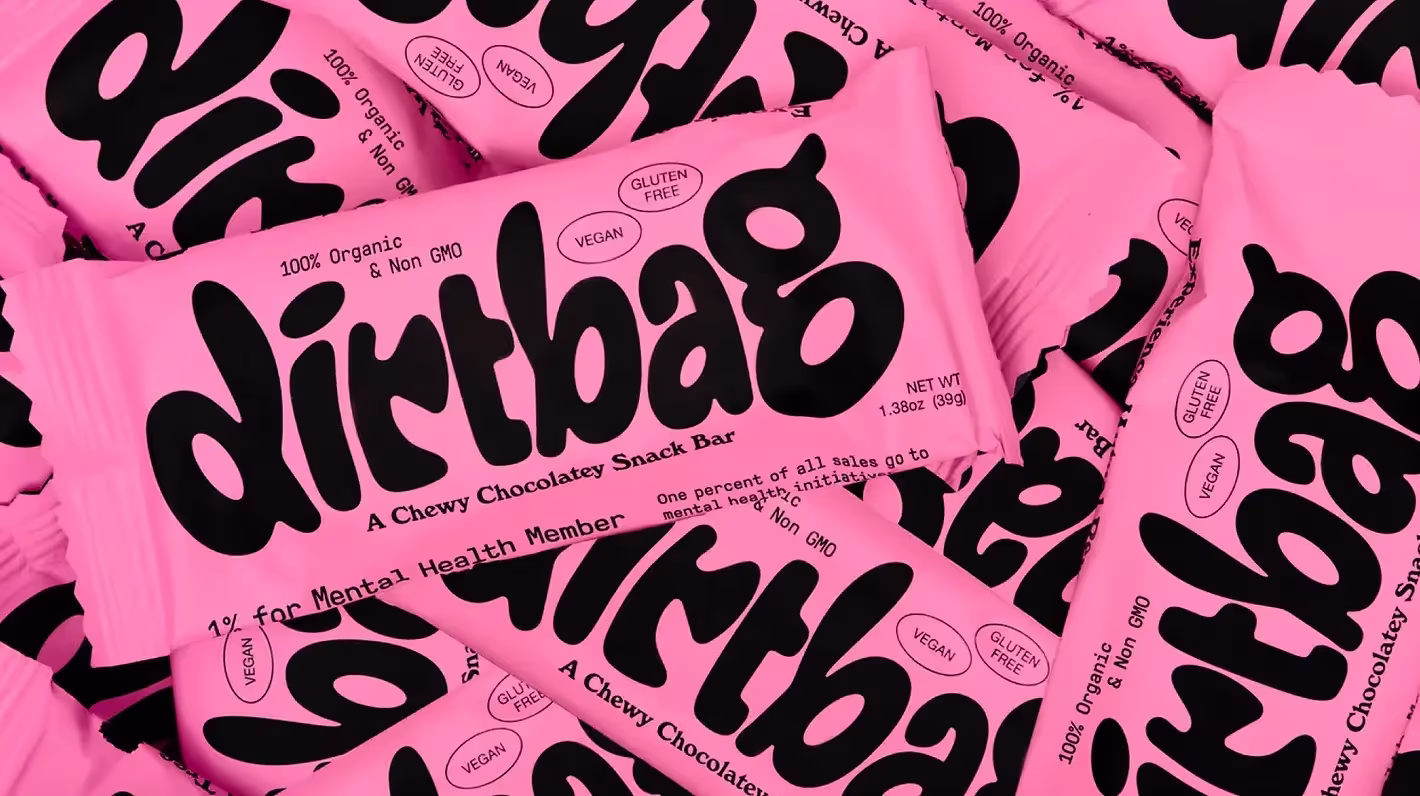
Пузырчатая типографика всех форм и размеров находится на пике популярности: приземистые надутые буквы и тягучие шрифты все чаще можно увидеть на логотипах как новых, так и уже давно существующих брендов.
Можно даже сказать, что мы живем в эпоху бума экспрессивных шрифтов. Да, многие из них состоят из округлых форм, но “пузырчатые шрифты” занимают отдельную нишу. В отличие от более обширной категории шрифтов “Югендстиль”, они почти никогда не содержат резких изгибов, узких штрихов или острых краев, которые бы уравновешивали их округлость. Они выделяются из толпы — приятные и дружелюбные на фоне откровенной серьезности брендинга прошлого десятилетия (и общего уныния пандемии).
Типографика, лежащая в основе этих пузырчатых форм, разнообразна: некоторые напоминают типичные модернистские шрифты без засечек, наполненные слишком большим количеством воздуха, в то время как другие больше похожи на традиционные рукописные шрифты, расплавившиеся под солнцем.
Эту тенденцию к более пышной типографике часто поддерживают бренды, которые используют яркие, насыщенные цветовые палитры, аналогичные округлые или пузырчатые шрифты для второстепенной типографики и другие органические элементы неправильной формы, такие как капли и волнистые линии.
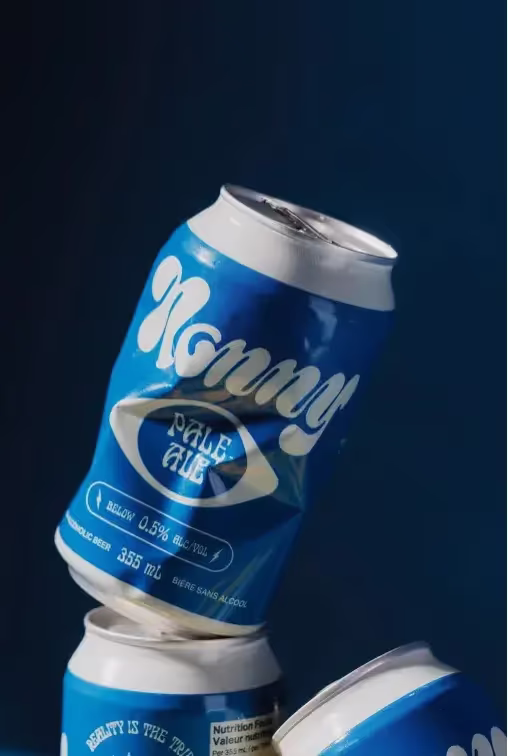
Сильное влияние на пузырчатые шрифты оказали их прямые предшественники канувшей в прошлое индустрии потребительских товаров (CPG): упаковки конфет и напитков 1970-х годов (или эпохи Вилли Вонки). Типографика того времени была уникальной и смелой, вероятнее всего, в ответ на более сдержанную эстетику середины 50-х и 60-х годов. Пример последней: стиль графического дизайнера Массимо Виньелли и упаковки потребительских товаров с минимумом цвета и модернистскими шрифтами без засечек в духе “Hersheys” (американская кондитерская компания), “M&M's” или “Life Savers” (бренд леденцов в форме колец).
Современная вариация выразительного, выпуклого шрифта — результат аналогичного реактивного импульса. Однако она появилась в ответ на претенциозную типографику без засечек в скандинавском стиле, которая доминировала в брендинге продуктов питания, напитков и БАД в 2010-х. Честно говоря, это была настоящая эра минимализма, вот несколько примеров: Casper, Outdoor Voices, Ritual.
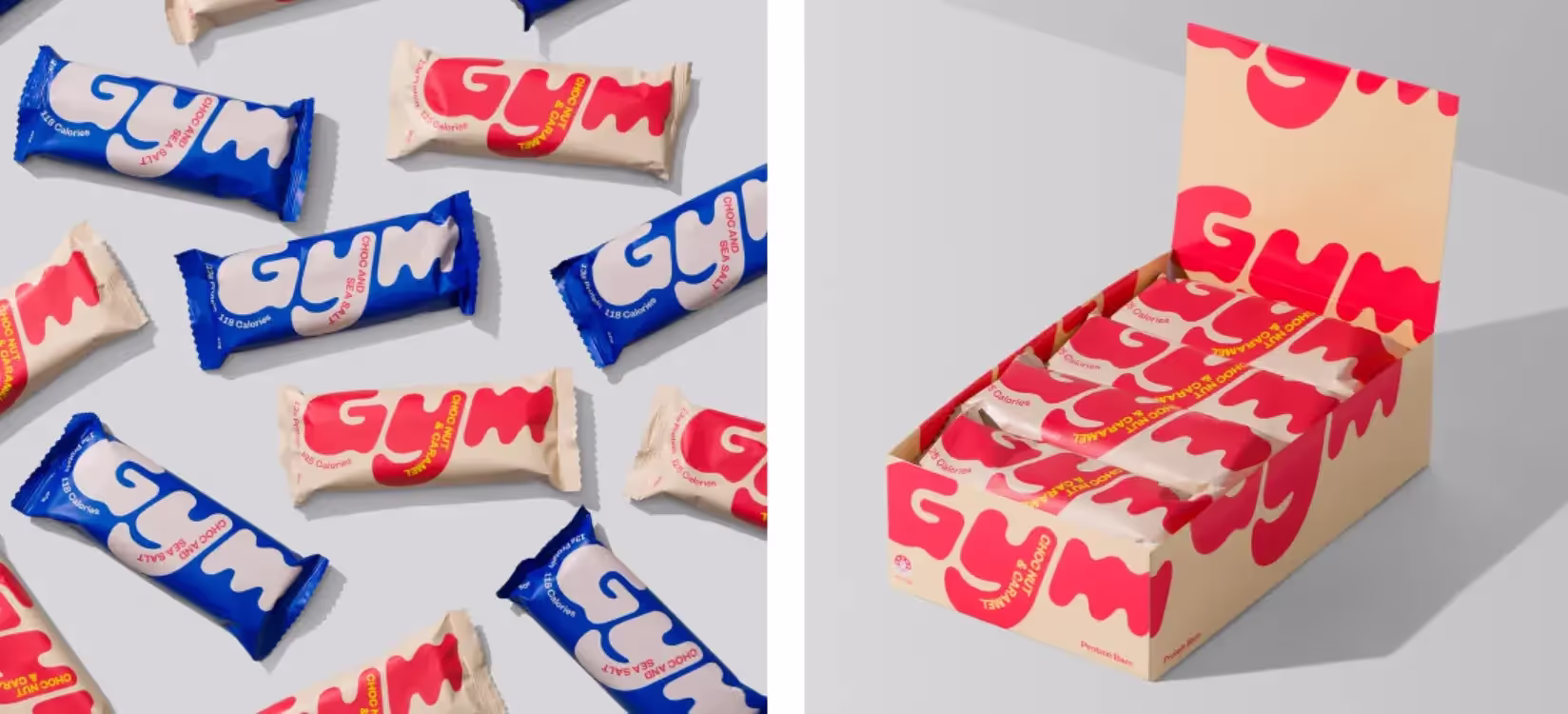
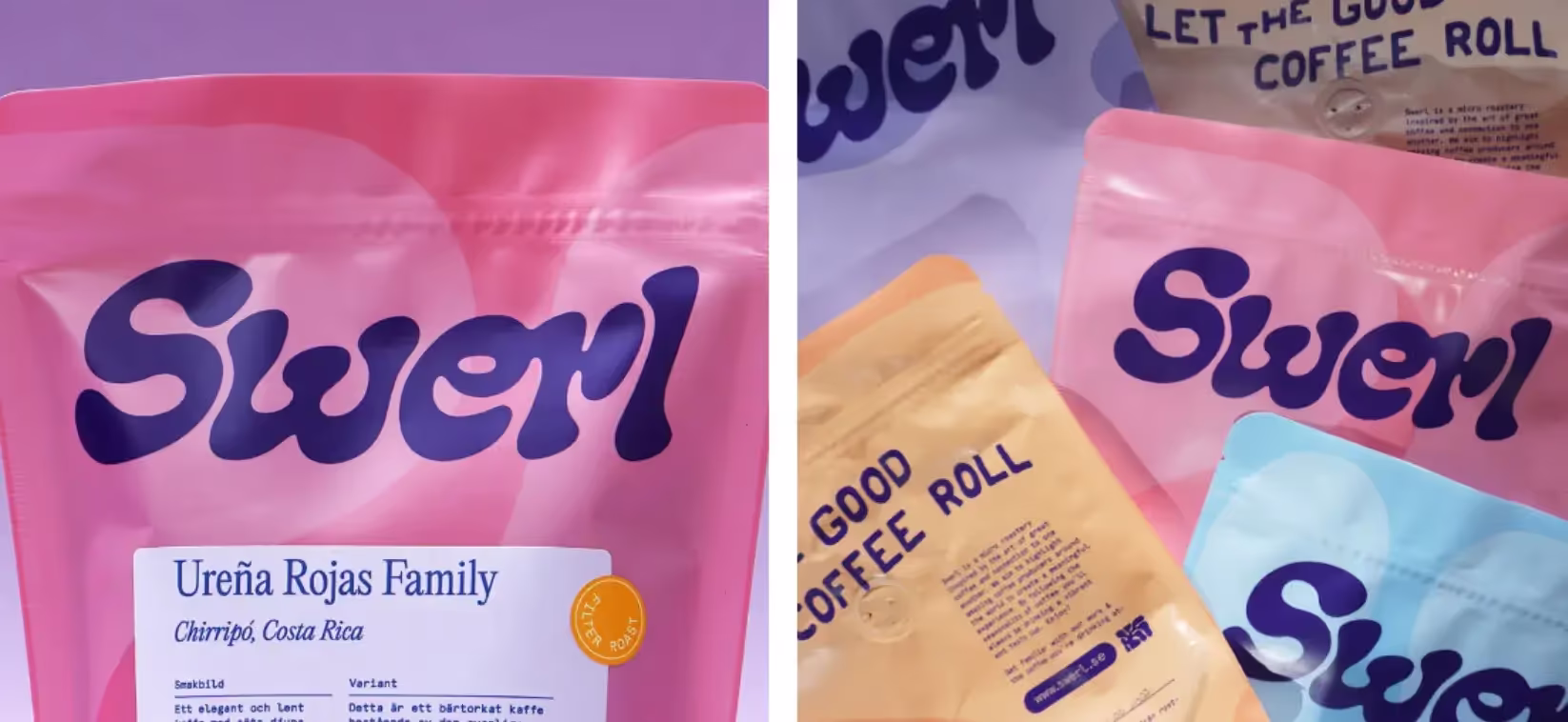
«Стиль 1960-х и 1970-х кажется современным потребителям знакомым и обнадеживающим, но в то же время свежим», — объясняет Джелисса Латини, которая разработала “пузырчатый” фирменный стиль для бельгийского шоколадного бренда Kyoot. Латини говорит, что ее идея состояла в том, чтобы добавить «дерзости» в зачастую излишне серьезный мир темного шоколада. Новый брендинг должен был дополнить его неожиданным легкомысленным ретро, не жертвуя при этом ощущением современности и крутости.
По словам Латини, пузырчатые шрифты бывают столь же универсальными, сколь и бунтарскими. Их можно использовать для чего угодно: от обложки винила до книги с рецептами или логотипа прачечной.
Пузырчатые шрифты могут отлично вписаться даже в айдентику солнцезащитных средств. Креативное агентство RoAndCo разработало фирменный стиль для нового бренда Bask. Его логотип напоминает набегающую волну (я помогала этому агентству в доработке логотипа и упаковки).
Креативный директор RoAndCo, Роанн Адамс, руководившая разработкой бренда, предполагает, что популярность эффектных, броских шрифтов — это не просто очередной тренд, а форма концептуального прогресса отрасли. Фирменный стиль не обязательно должен быть строгим, чтобы отражать серьезные ценности бренда: «Мы стали более грамотными и любопытными потребителями. Да, мы по-прежнему заполняем наши кухни и ванные комнаты качественными продуктами — просто теперь мы не гоняемся за одной и той же строгой, минималистичной эстетикой».
Тренд на пузырчатые шрифты прослеживается во всех сферах: от моды до средств массовой информации (вспомните логотип бренда корректирующего белья от Ким Кардашьян “Skims” и логотип продюсерской компании Наоми Осаки “Hana Kuma”). Однако особенно ярко он проявляется в айдентике потребительских товаров — продуктов питания, напитков и косметики — в частности, тех продуктов, которые люди преимущественно употребляют на ходу, таких как желе в стаканчиках, протеиновые батончики или напитки в банках.
Это не случайно. До появления Интернета и, соответственно, онлайн-магазинов (примерно два десятилетия прогресса, если начать отсчет с момента основания Amazon в 1995 году) полки продуктовых магазинов и кладовые друзей были двумя основными способами знакомства с брендами.
Переход к прямым продажам в 2010-х годах взорвал эту модель, сделав основной точкой контакта потребителей с товарами веб-сайты, а не упаковку на полках магазинов. Но по мере развития социальных сетей брендам стало сложнее контролировать свой визуальный мир — их фирменные стили быстро ушли на второй план, подстроившись под формат и айдентику соответствующих приложений. Нужно было найти другой способ привлечь внимание потребителей.
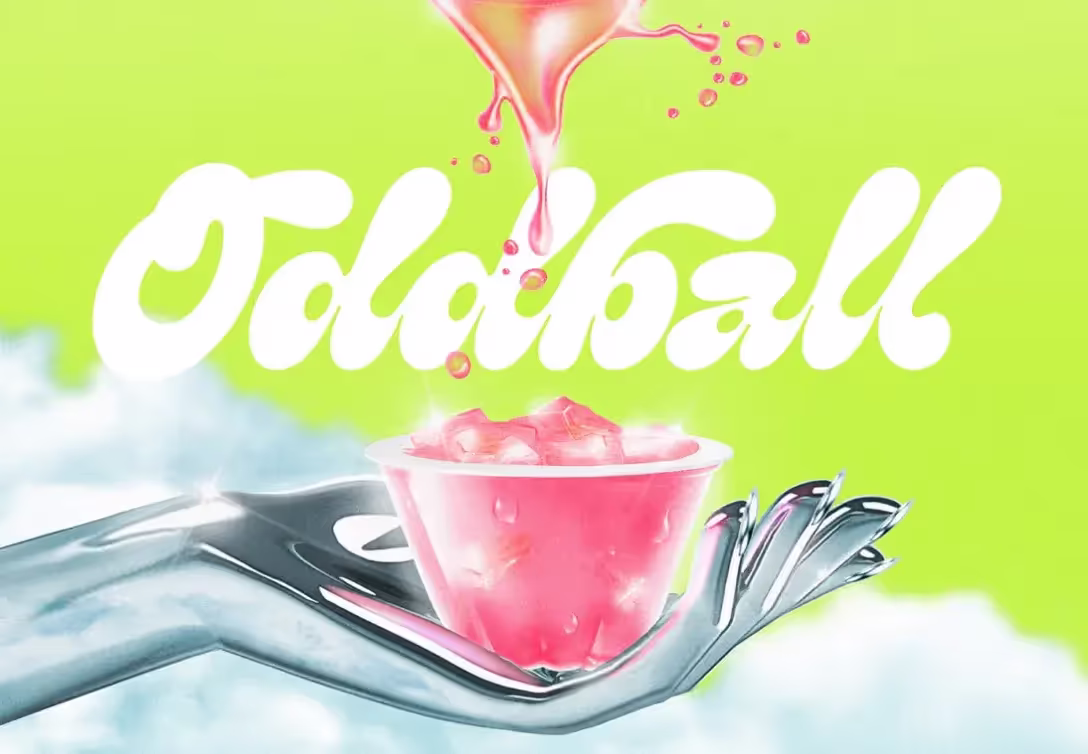
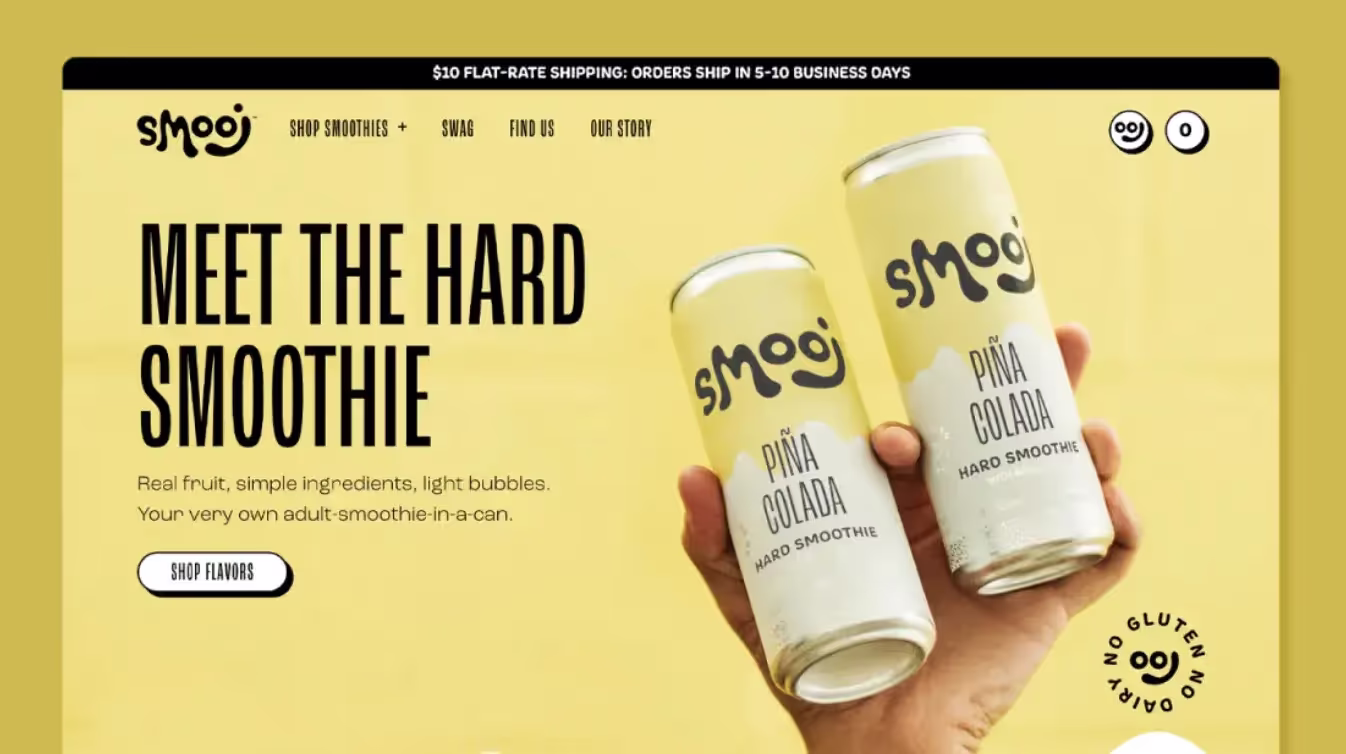
Возможно, это также одна из важнейших причин популярности пузырчатой типографики: все, что ассоциируется с каракулями, которые мы рисовали в юности на партах или в школьных тетрадях, выглядит дружелюбно и честно, вызывает чувство спокойствия и обнадеживает. А это верный способ установить связь и построить доверительные отношения с аудиторией в сверхнасыщенной и чреватой опасностями экосистеме современных брендов.